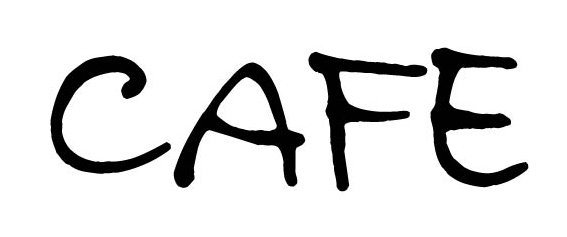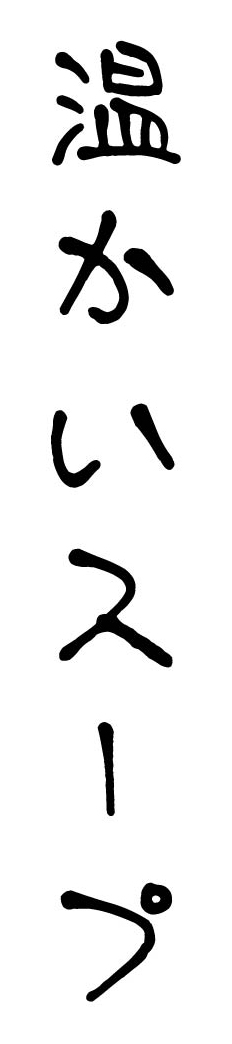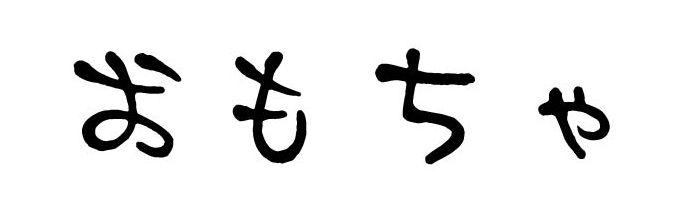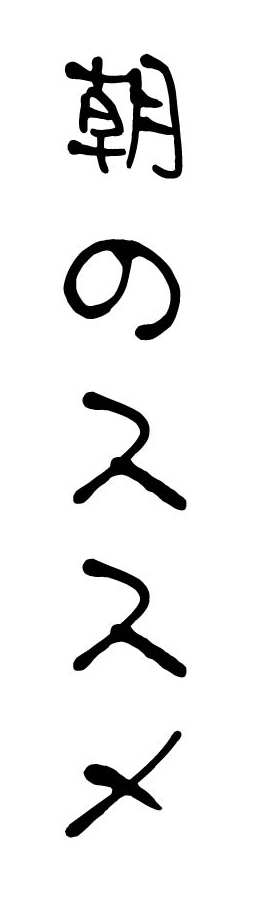
デザイン筆文字フォント 雨点 (ダウンロード版)
【書:高瀬あゆみ】
このフォントは弊社書籍『デザイン筆文字シリーズ5雨点』(高瀬あゆみ 著)を、株式会社武蔵システムがフォント化したものです。手書きの温かみのある書体は、ポスターやメニュー、同人誌の表紙など、あらゆる場面でお使いいただけます。フォントフォーマットは、TrueTypeとOpenTypeです。1ライセンスに両方含まれます。印刷物への使用など一般的な商業利用は追加料金なしで可能です。詳細については、上記リンク「使用許諾範囲」を、ご購入前に必ずご確認ください。
・「、」や「。」促音の「っ」や「ッ」などは文字組を考慮して文字位置を調整しています。一部の文字は仮想ボディをはみ出しているため、TrueTypeフォントを使って縦書きした場合、左右に仮想ボディをはみ出している部分が表示されないことがあります。その場合はOpenTypeフォントを使ってください。